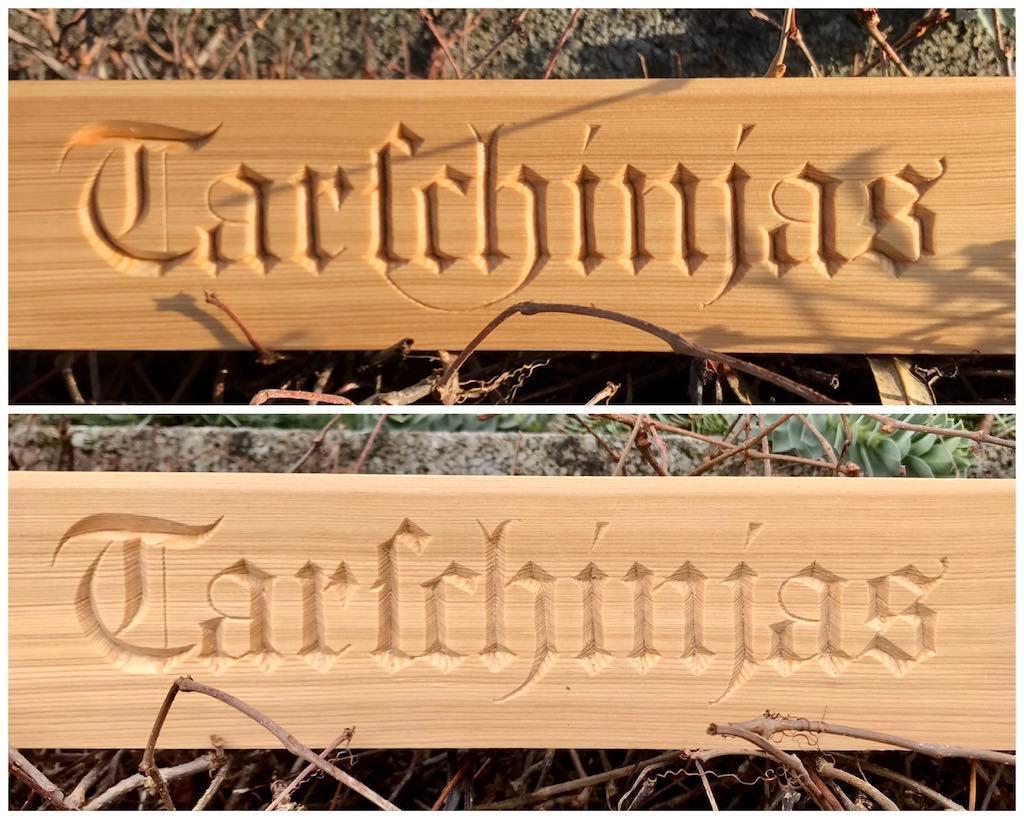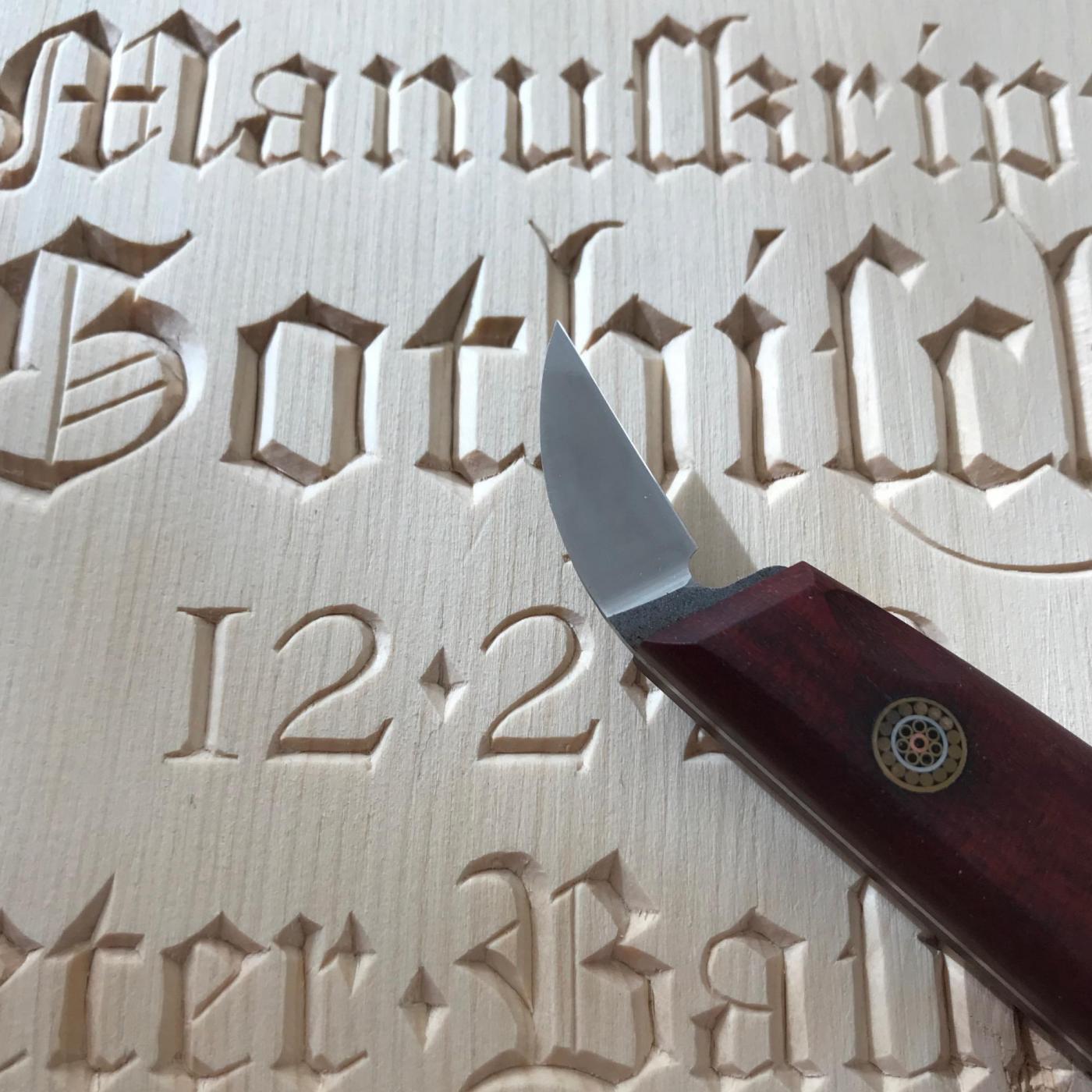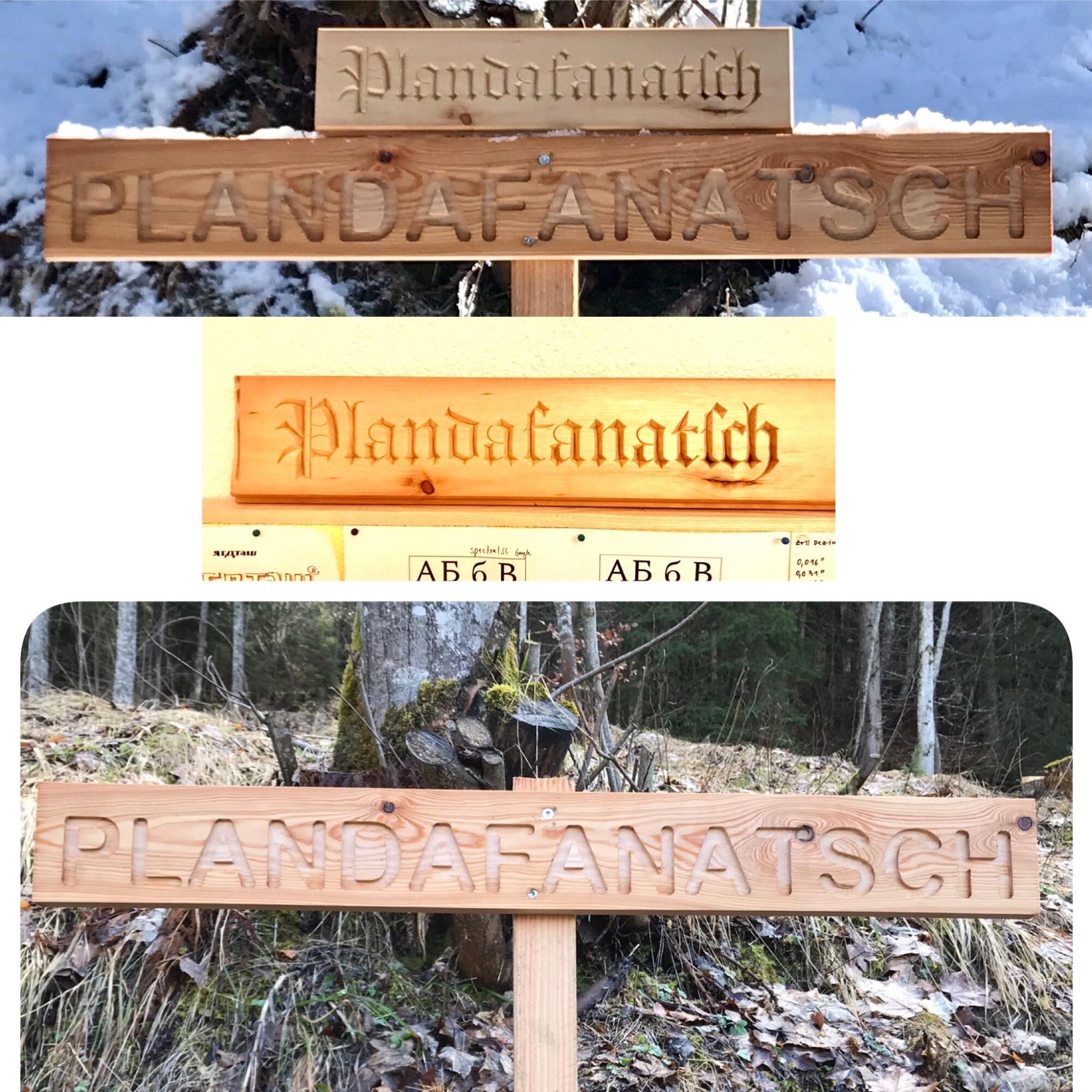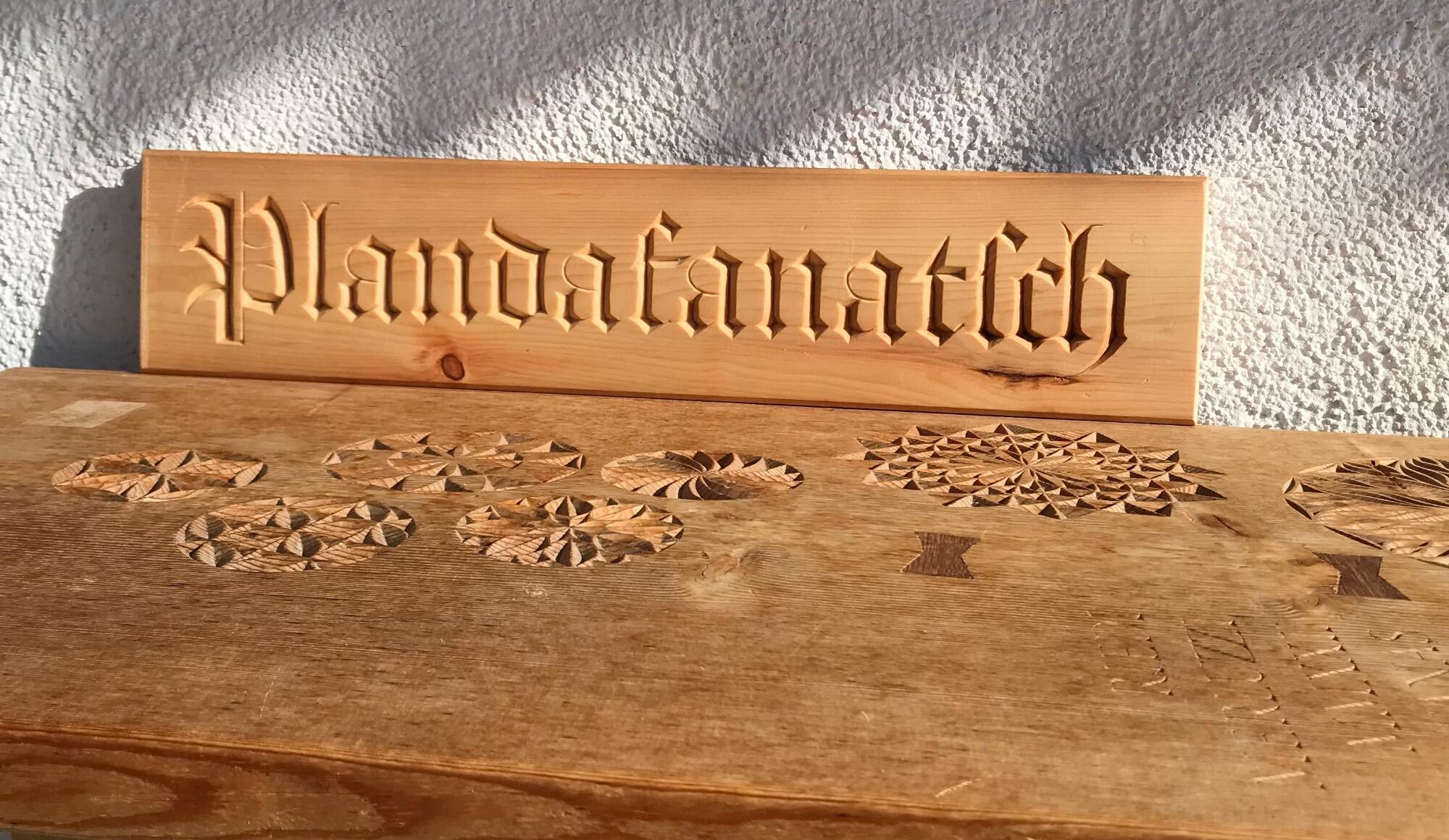
Manuskript Gotisch in Lärche geschnitzt
Kerbschnitzerei-Versuch in Lärche für ein paar Flurnamenstäfelchen. Oben im Bild mit Holzbutter behandelt, unten naturbelassen. Holzbutter ergibt – speziell auch im Zusammenspiel mit der tiefstehenden Nachmittagssonne – eine bessere Lesbarkeit, dank mehr Kontrast und klareren Konturen. Der erste Versuch dient vor allem dazu, den besten Schleifwinkelkompromiss der Schnitzmesserklinge für dieses harte Holz zu ermitteln. Darum stimmen auch nicht alle Winkel der Schnitzerei; vor allem sichtbar durch das tiefer ins Holz geschnittene Lang-s. Und auch die Schnittrichtungen sind noch zweifelhaft (ungelenker Kopfbalken auf dem "T" etc.). Aber insgesamt ist die Manuskript Gotisch eine geeignete Kerbschnitzschrift – meines Erachtens.
Brettchen ca. 70 mm hoch, Versalhöhe Manuskript Gotisch ca. 41 mmtarschinjas.jpeg.cab32f7c75485a14d122c14aaa87e513.jpeg
Zur Kerbschnitzerei kam ich, weil ich Messergriffe französischer Messer selber machen/schnitzen/verzieren wollte und auf der Suche nach passenden Schnitzmessern für diese Tätigkeit war. Dabei stiess ich auf die Marken Pfeil (Kerbschnittmesser) und Klötzli (Modell 2). Beide schmieden hervorragende Qualitätsmesser.
Die Sujets und Schriften zeichne ich entweder direkt auf's Holz oder drucke sie ab einem Schwarzweiss-Laserprinter aus Word auf Papier (die ganzen Adobe-Profiprogrammverträge habe ich mit der Pension gekündigt), um dieses als Vorlage mit einem Pritt-Klebestift satt und ganzflächig auf's Holz zu kleben. Diese Vorgehensweise hat den Vorteil sehr präziser Linienvorlagen. Nachteile sind: der genaue Verlauf der Holzfasern ist während der Schnitzarbeit nicht erkenntlich. Das erschwert eine präzise Schnittführung (möglichst mit der Faser schneiden); und das Papier soll schlussendlich wieder entfernt werden … da kommt Wasser ins Spiel … das ist schlecht für's Holz ... es ist ein Abwägen und etwas Erfahrung.
Holz: Linde für's Feine, aber auch sehr gerne Arve (Zirbe in Österreich), sehr schön ist Olive (sehr hart, weitaus härter als Eiche;), Fichte/Tanne, Lärche, Eiche auch (fasrig,hart), Nussbaum, Ahorn (hart).
(Bis auf die Messer sind alles Übungsbrettchen. Die zersäge ich nachher zu Behältnissen. Oder ich trenne sie auf und handhoble sie rückseitig auf ein postalisch passendes Gewicht herunter, damit ich sie als "Karte" verschicken kann. )
Übrigens … zur Ausführung gelangte eine CNC-gefräste Version (siehe Bildmontage mit dem direkten Vergleich zuoberst). Meine handgeschnitzte Gratisvariante war "zu klein".